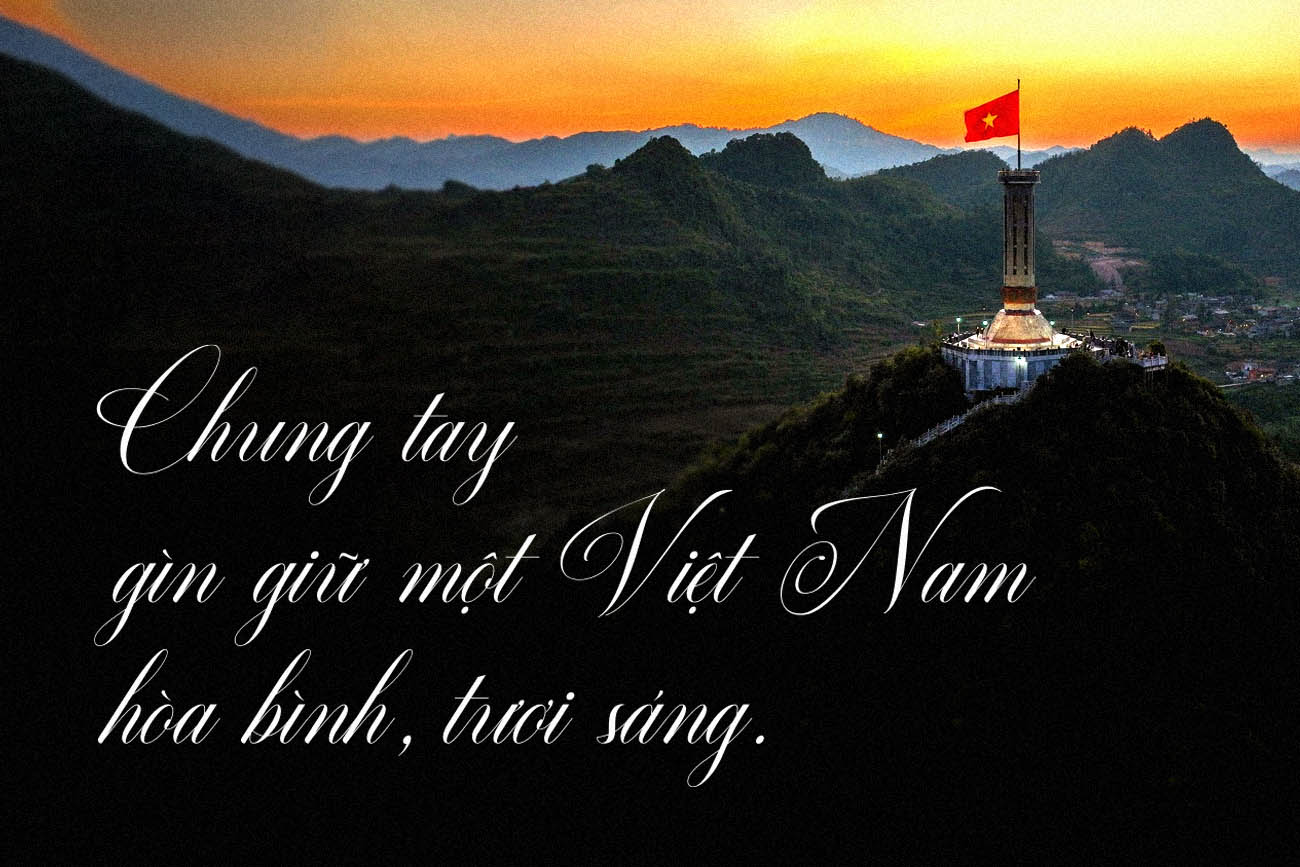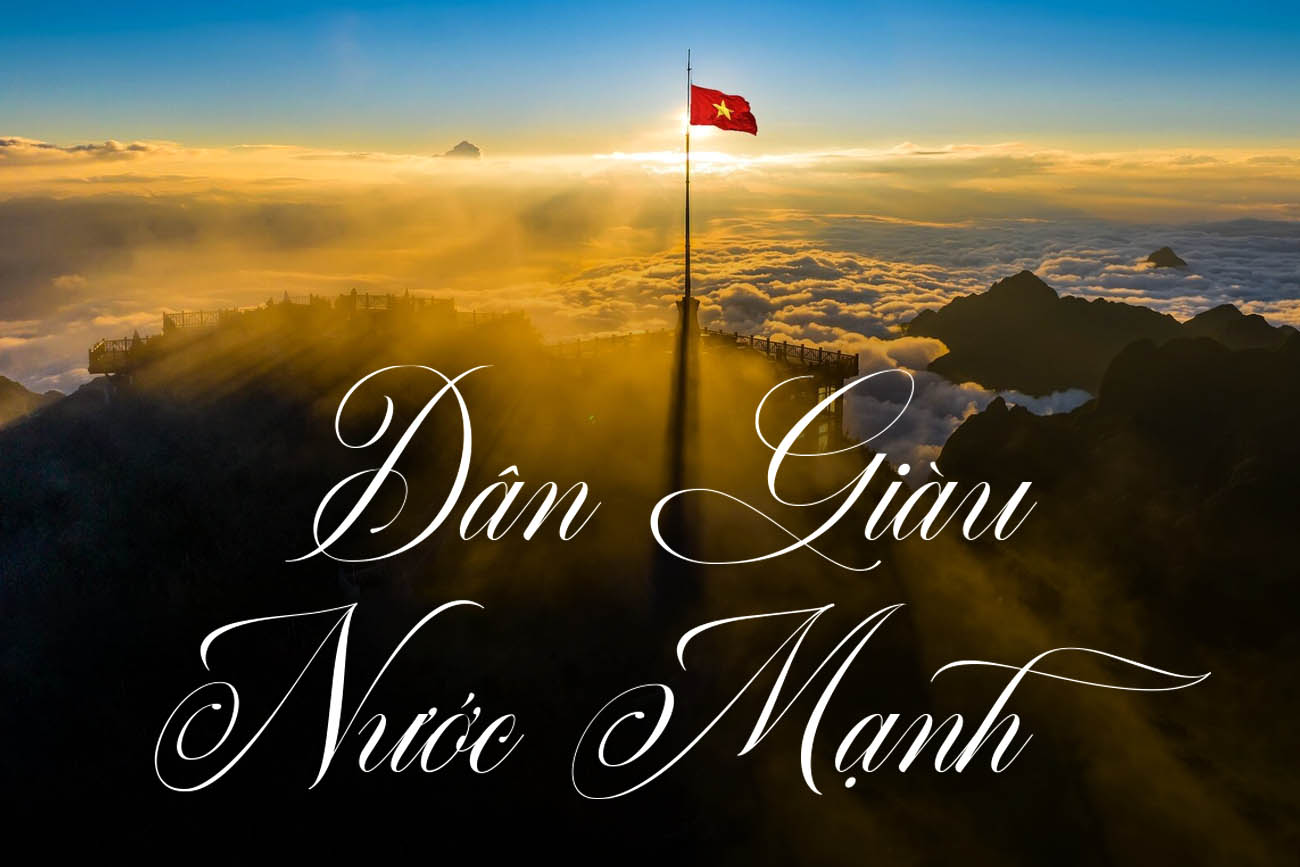
Font chữ Việt hóa cho ngày cưới TH Quadrien Script
Trong thế giới thiết kế đồ họa, việc tìm kiếm một kiểu chữ thể hiện được sự tinh tế, thanh lịch và mang lại cảm xúc cho người xem luôn là ưu tiên hàng đầu. Hôm nay, chúng tôi xin giới thiệu đến cộng đồng designer bộ phông chữ TH Quadrien. Đây là phiên bản được chăm chút kỹ lưỡng, bắt nguồn từ tác phẩm gốc Quadrien của nhà thiết kế tài năng Ramzehhh
Vẻ đẹp nguyên bản của một font chữ Script tinh tế
TH Quadrien mang trong mình hơi thở lãng mạn và nghệ thuật. Điểm thu hút nhất của bộ phông chữ này chính là sự chuyển đổi mượt mà giữa các nét thanh và nét đậm. Với đặc trưng là một font chữ Script cao cấp, từng ký tự được thiết kế với độ nghiêng hoàn hảo, tạo ra nhịp điệu thị giác vô cùng bắt mắt.
Bên cạnh đó, cấu trúc của một font chữ uốn lượn mềm mại giúp TH Quadrien phá vỡ đi sự cứng nhắc của các văn bản thông thường. Những đường nét bay bổng ở phần đuôi chữ được nhà thiết kế Ramzehhh tính toán tỉ mỉ, giúp các tác phẩm typography của bạn trở nên có hồn, nghệ thuật và thu hút ánh nhìn ngay từ giây phút đầu tiên.
Lựa chọn số một cho các dự án lãng mạn
Nhờ vào sự thanh lịch và sang trọng vốn có, TH Quadrien là sự lựa chọn không thể tuyệt vời hơn khi bạn đang tìm kiếm một font chữ đám cưới. Từ thiệp mời, bảng tên cô dâu chú rể, menu tiệc cưới cho đến các ấn phẩm nhận diện thương hiệu cao cấp, bao bì mỹ phẩm hay logo dạng chữ ký, phông chữ này đều đáp ứng một cách xuất sắc. Sự kết hợp giữa TH Quadrien và các phông chữ Serif hoặc Sans-Serif tối giản sẽ tạo nên một tổng thể thiết kế vô cùng đẳng cấp.
Dấu ấn Việt hóa từ TH Team
Để mang vẻ đẹp của Quadrien đến gần hơn với các nhà thiết kế Việt, TH Team đã tiến hành Việt hóa trọn vẹn bộ phông chữ này dưới cái tên TH Quadrien. Là một đơn vị uy tín trong cộng đồng, TH Team đã dành nhiều tâm huyết để tinh chỉnh từng dấu câu, từng ký tự có dấu sao cho hài hòa tuyệt đối với đường nét của bản gốc. Các designer giờ đây có thể thoải mái sáng tạo nội dung tiếng Việt mà không còn lo lắng về tình trạng lỗi font hay lệch dấu làm mất đi giá trị thẩm mỹ của tác phẩm.
TH Quadrien không chỉ giữ trọn vẹn vẻ đẹp nguyên bản mà còn phá bỏ rào cản ngôn ngữ, trở thành công cụ đắc lực cho mọi dự án đồ họa. Bạn có thể tham khảo chi tiết phong cách của phông chữ gốc tại [Quadrian Elegant Script](https://elements.envato.com/fr/quadrian-elegant-script-WD6AQZN) để tìm thêm nguồn cảm hứng trước khi tự mình trải nghiệm phiên bản Việt hóa tuyệt vời này từ TH Team.